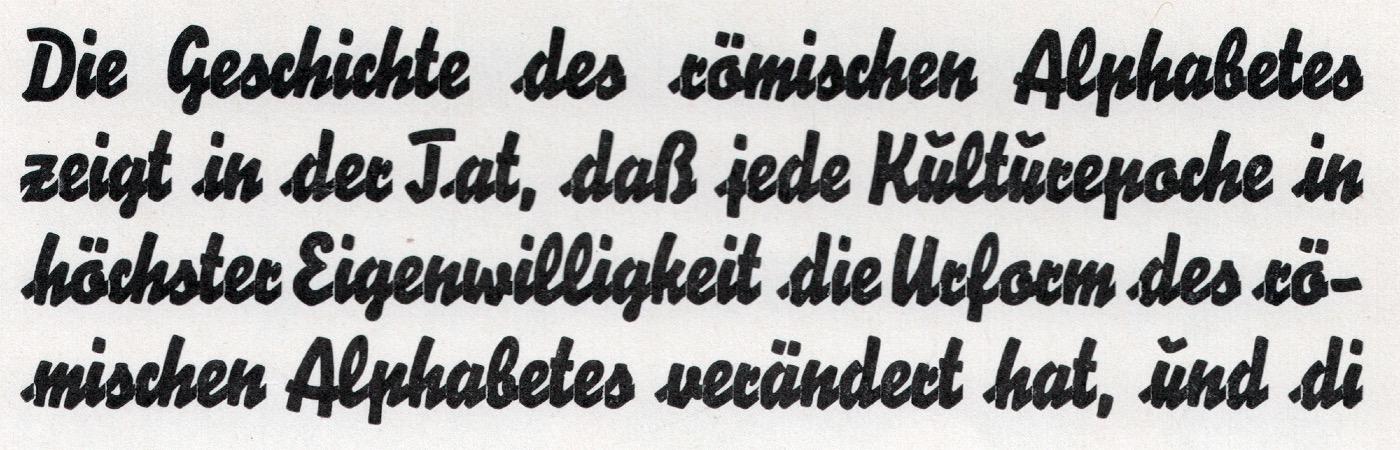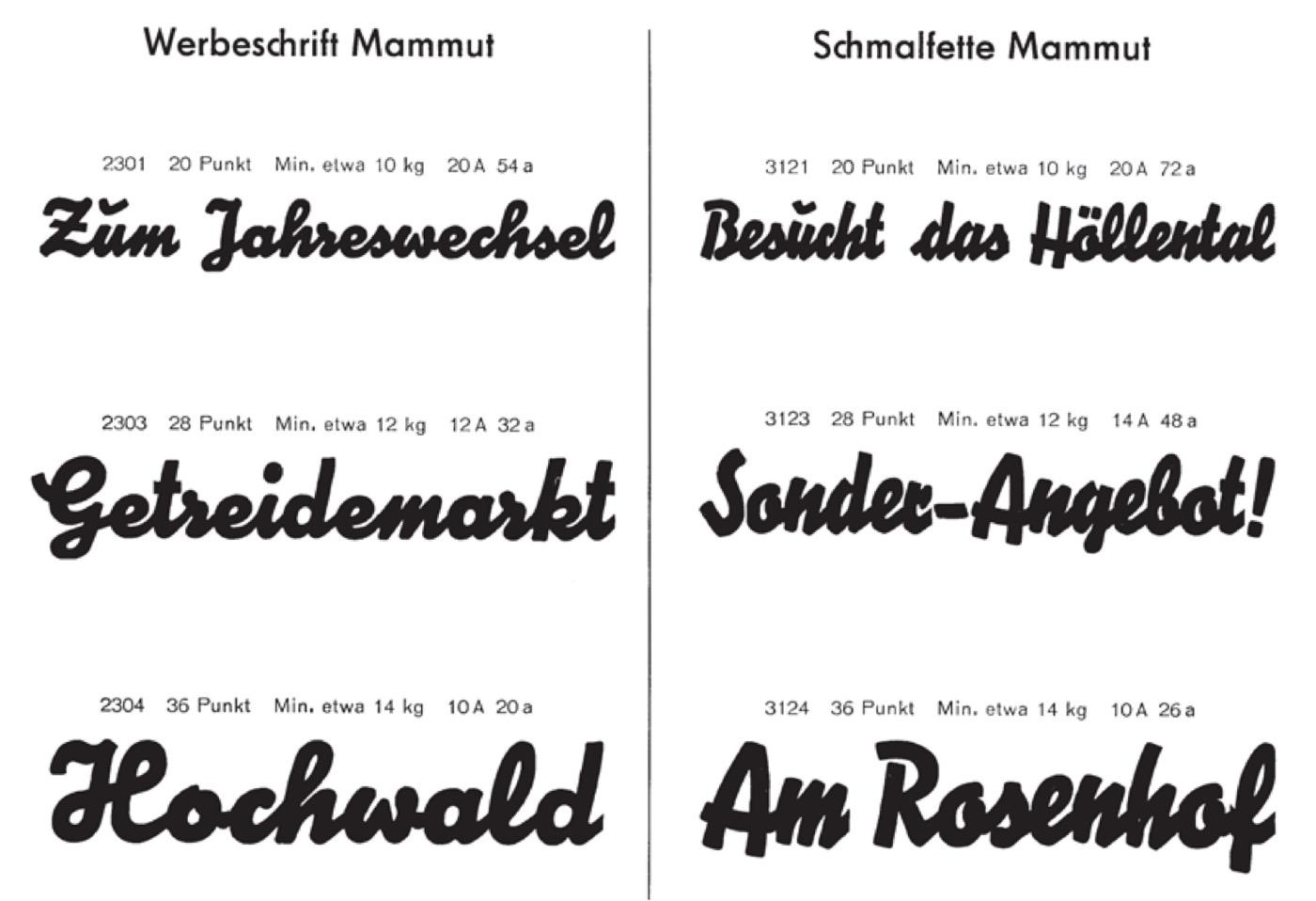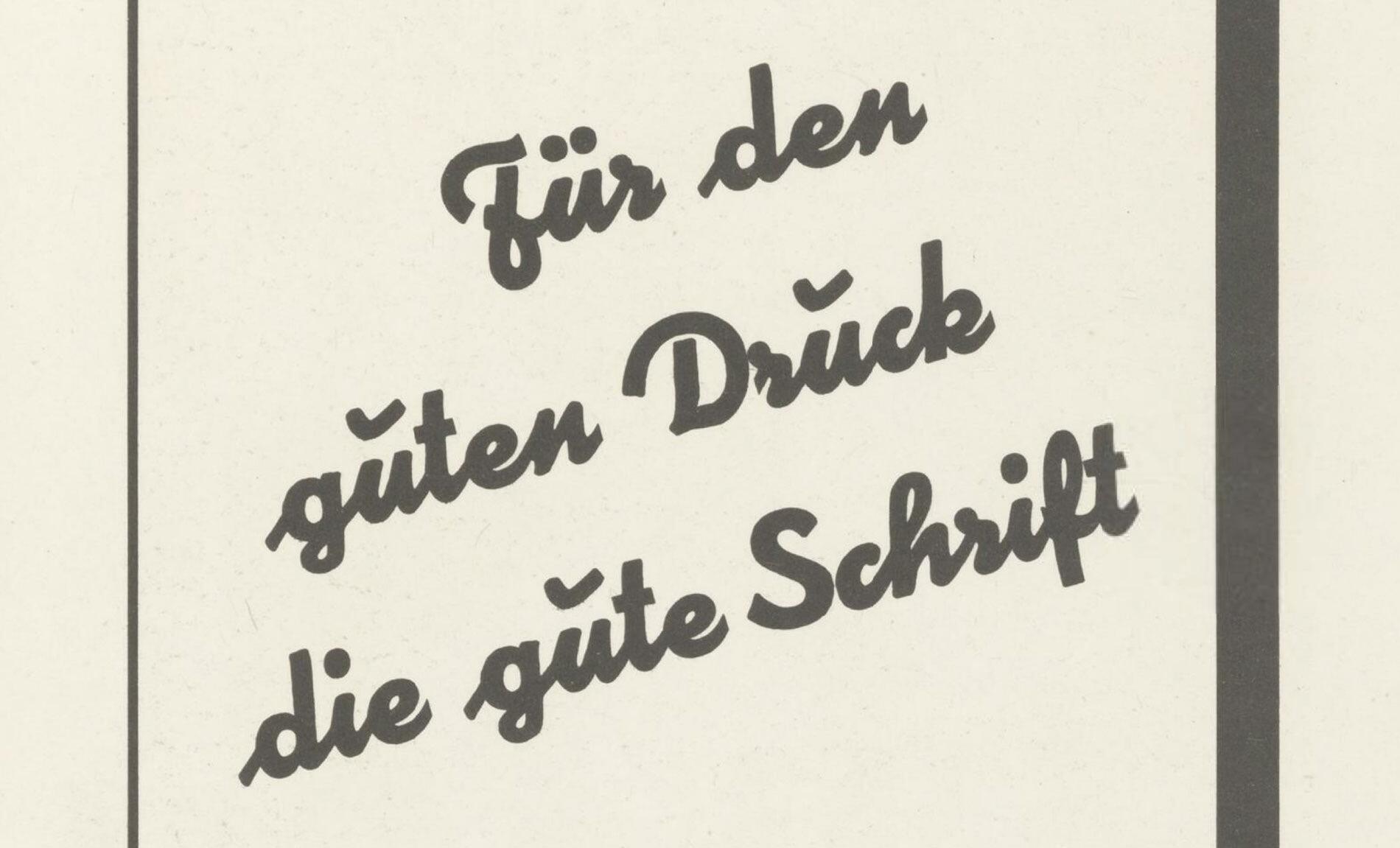
- 1928
- Antiqua Schreibschrift
Die Werbeschrift Mammut erschien Ende der 1920er-Jahre bei der Schriftgießerei Ludwig Wagner. 1932 wurde der Schrift eine schmalfette Version zur Seite gestellt. Diese ähnelte jedoch Bertholds Block-Signal, für die im Frühjahr des gleichen Jahres Musterschutz beantragt wurde. Berthold verklagte die Gießerei Wagner daraufhin auf Unterlassung und Schadensersatz.
Schmalfette Mammut. Figurenverzeichnis
Schmalfette Mammut. Satzbeispiel
Gegenüberstellung. Mammut 1928 | 1932